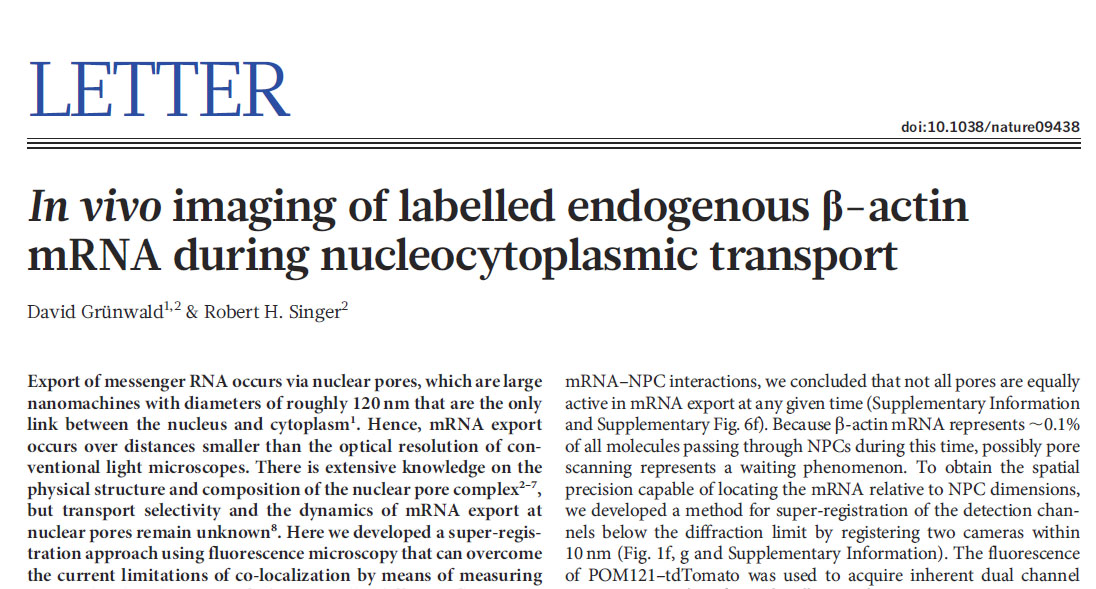
Just for fun – Quiz
Gerade erst bin ich darüber gestolpert, daß das Wissenschaftsmagazin »nature« die vorher serifenlosen Überschriften geändert hat. Ich war mir ziemlich sicher, daß ich die Schrift nicht kenne und auch vorher noch nicht bewußt gesehen habe. Trotzdem kam sie mir merkwürdig vertraut vor. Im Nachhinein ist mir klar daß ich durchaus hätte erraten können, wer der Gestalter dieser Schrift ist.
What the font hat mit dem gezeigten Beispiel keine Probleme, das gilt also nicht! Es ist das zielsichere Erkennen einer »Handschrift« gefragt. Wer erkennt die Schrift vom bloßen Hinsehen? Oder nennt mir zumindest den Schriftgestalter? (Den Fließtext meine ich natürlich nicht ...)
Und weil es so schön ist: wie findet Ihr das Layout generell und die Kombination der Schriften?
nettes rätsel, nettes layout. mein erster gedanke war richtig, wie ich via whatthefont überprüfen konnte. das ›a‹ war für mich relativ aussagekräftig.
nicht richtig ist kris sowersby, an dessen tiempos text mich die überschriften vage erinnerten. auch nicht richtig sind zwei andere ältere herren, die mir als erste durch den kopf schossen – aber dann erschien mir die schriftart zu modern.
das spoilern überlasse ich dann mal anderen …
nettes layout.
Findest Du? Mir gefällt es nicht – vorallem die Kombination der Schriften. Den Titel finde ich an sich schon gut – aber zusammen mit der Minion? Für mich ist das irgendwie als ob man zur schwarzen Hose einen dunkelblauen Blazer trägt – man ist sich nie sicher ob es in der morgendlichen Dunkelheit einfach ein Versehen gewesen ist oder tatsächlich Absicht. Ich hätte mir ja zu der Überschrift auch eine modernere Textschrift gewünscht.
Das »LETTER« sieht m.E. ganz furchtbar auch – im Druck noch schlimmer als auf dem Monitor. Und die dreifache Linie finde ich völlig unmotiviert. Was soll das?
Spaßenshalber hier mal eine ältere Version:
Da kann man sich auch jede Menge meckern, aber »altbackener« finde ich persönlich das beileibe nicht.
Das LETTER entspringt dem selben Font wie die Überschrift, ist also wahrscheinlich Absicht, um nicht noch einen dritten Font zu verwenden. Es sieht trotzdem nicht gut aus, da bin ich bei dir.
Das LETTER entspringt dem selben Font wie die Überschrift, ...
Siehst Du das oder hast Du nachgesehen?
Ich persönlich hätte das ja »klassischer« gehandhabt: ich hätte den Medium-Schnitt genommen, alles in kleinen Kapitälchen gesetzt und kräftig gesperrt. Das wäre zumindest weniger staksig gewesen als die derzeitige Variante.
Aber das ist nur mein persönlicher Geschmack.
Mir gefällt die ältere Variante auch besser als die neue ... Die alte war sicherlich nicht perfekt, aber ... unauffällig, die neue ... das fällt genau in mein Klischee von wissenschaftlichen Texten ... ;) Irgendwie steif und technisch und unelegant ... :?
Findest Du? Mir gefällt es nicht – vorallem die Kombination der Schriften. Den Titel finde ich an sich schon gut – aber zusammen mit der Minion?
oh, das habe ich nicht gesehen bzw. nicht genau genug hingesehen. ich bin davon ausgegangen, dass jetzt (praktisch) alles in der neuen schrift gesetzt ist. wäre das so, würde ich bei meinem urteil bleiben. so wie es tatsächlich ist, trifft dein anzugvergleich aber zu.
Das LETTER entspringt dem selben Font wie die Überschrift, ...
Siehst Du das oder hast Du nachgesehen? …
Nachgeschaut, ich hab ihn nicht erkannt.
Nein, ich meinte ob Du das gesehen hast, daß es der gleiche Font ist? Oder hast Du beide getrennt nachgeschaut und dann erst festgestellt, daß what the font den gleichen Font angibt? :wink:
So wie ich? :|
Ich hab bei wtf nachgeschaut und – da zufällig ein E im angezeigten Beispiel war – festgestellt, dass das wohl die gleiche Familie ist. So wie die beiden Schriften im Beispiel untereinanderstehen wäre ich nicht draufgekommen, dafür sind die leichten Versalien optisch zu weit weg von den fetten Gemeinen.